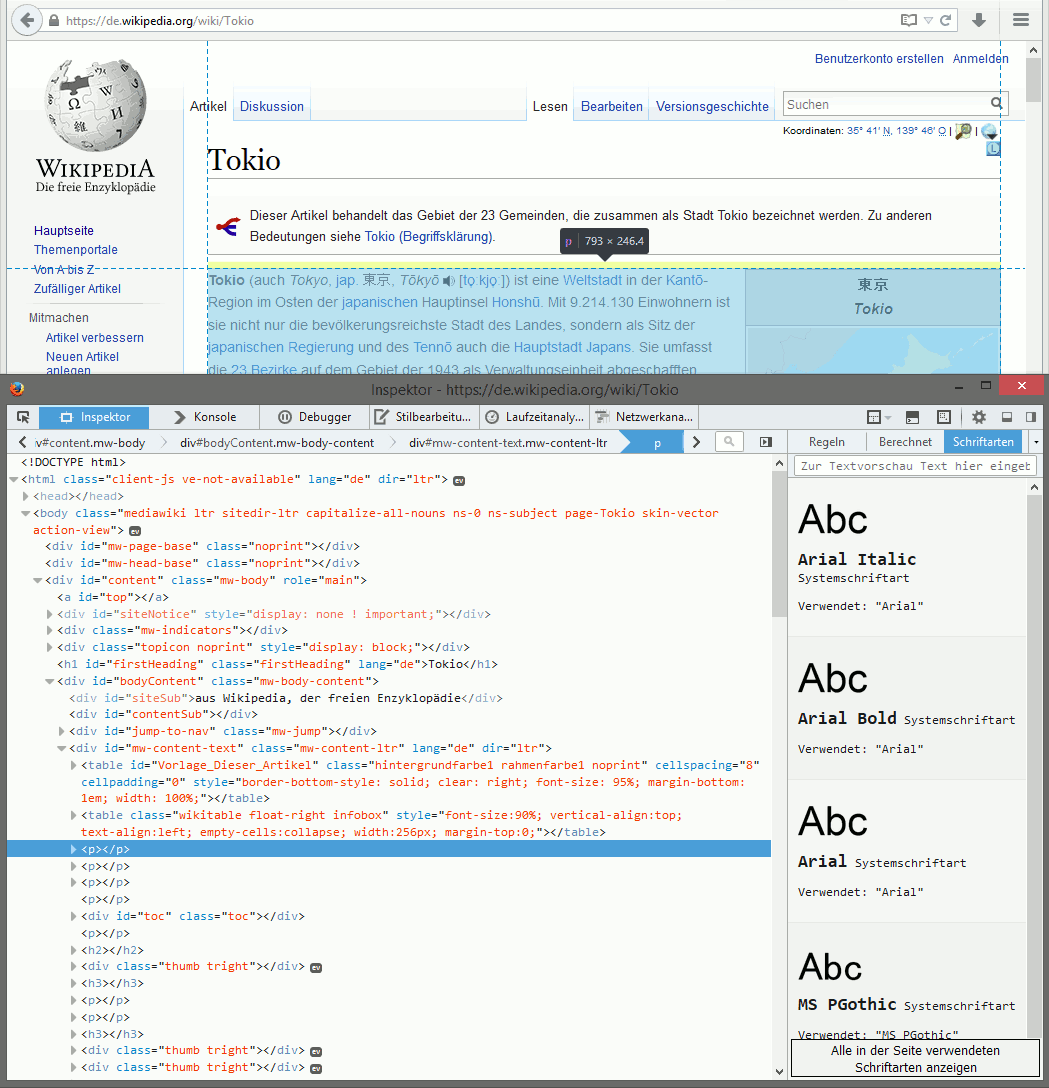
Welche genaue Schriftart verwendet Wikipedia in den Artikeln?
ich möchte wissen, welche Schriftart (mit welchen Einstellungen/Formatierungen) in Wikipedia in den Artikeln verwendet wird.
Also nicht die Logoschrift, Überschriften, Überüberschriften, sondern der ganz normale Artikeltext.
Ein Ergebnis konnte ich im Internet schon dazu finden (Antwort #2), aber ich verstehe es nicht genau:
Welche Schriftart bzw. Einstellung ist es denn nun? Da steht "Sans-Serif", aber wenn ich im Internet wiederum danach schaue, dann kommen da verschiedene Schriftarten. Gibt es eine Font zu der Wikipedia-Artikel Schrift? Oder eine PSD-Vorlage?
Ich möchte/muss sie nämlich ohnehin in Photoshop verwenden.
Ich bin etwas schwer von Verstand wenn es um so etwas geht.
sans-serif ist eine generelle Styleanweisung, die sagt dass der Browser hier die Systemweite sans-serif-Schrift verwenden soll. Welche das genau ist müsstest du bei deinem System selbst nachschauen.
Um auf Webseiten die Schrift herauszufinden kannst du in Firefox einfach auf "Element untersuchen" gehen, und dort dann auf "Schriftarten"
Ich habe eine Erklärung gefunden, die vielleicht etwas aufschlussreicher ist. Wikipedia verwendet eine Sammlung von Fonts, in absteigender Reihenfolge. Will heißen sollte das anzeigende System über den gewünschten Font nicht verfügen, so wird die Reihe durchprobiert bis ein Font dabei ist, der installiert ist. Das ist gerade dann wichtig, wenn man die Seite vielleicht mit einem Linux basierten System aufruft etc.
Sans-serif: Helvetica Neue > Helvetica > Arimo > Liberation Sans > Lucida Grande > sans-serif
Serif: Times > Georgia >Linux Libertine > Cambria > serif
Also ich verwende Microsoft Edge. Ich weiß nur, dass die Schriftart wahrscheinlich noch nicht auf meinem Computer ist, da ich sie nicht in Word einfügen kann. Wahrscheinlich ist es eine, die etwas kostet.
Dann muss es wohl auch nicht 1:1 die gleiche sein, aber eine die zum verwechseln ähnlich ist.
Bei mir sieht sie zumindest so aus:
Wenn ich jetzt zum Beispiel Calibri verwende, dann sieht diese immer noch zu anders aus.
Ich teste mal "WhatTheFont"
Da bekomme ich nur welche angezeigt, die total anders aussehen
Das wird ein Standard-Schrift sien, vermutlich also:
Arial, Lucida, Verdana. Ich tippe auf Arial.
Nur das Schriftbild muss gleich sein. Der Buchstaben-/Wörter-/Zeilen-Abstand ist wieder eine andere, schriftunabhängige Sache.
Sans-Serif bedeutet übrigens nur sinngemäß eine "schnörkelfreie Schrift". Times New Roman ist z.B. mit Schnörkeln besetzt.
BTW: Im Screen steckt ziemlich viel Clear-Type-Matsch drin (aktivierte Kantenglättung)